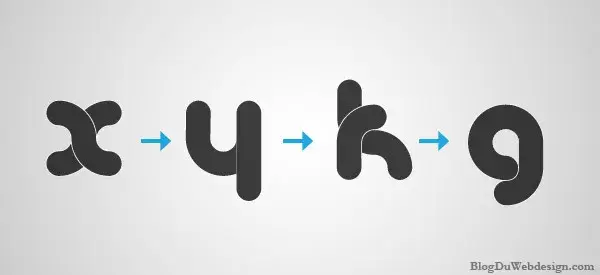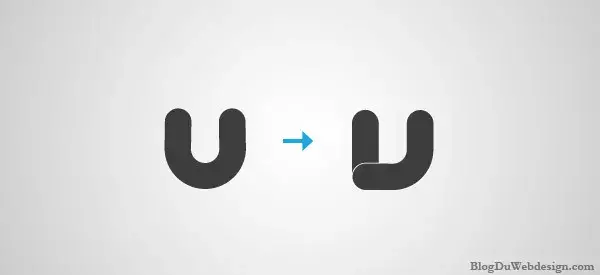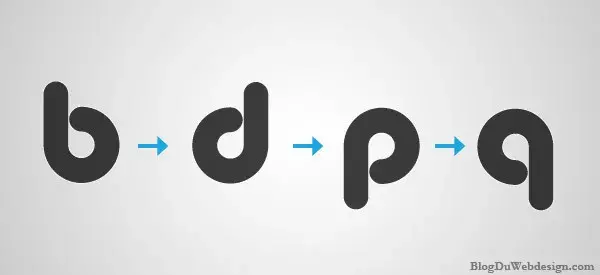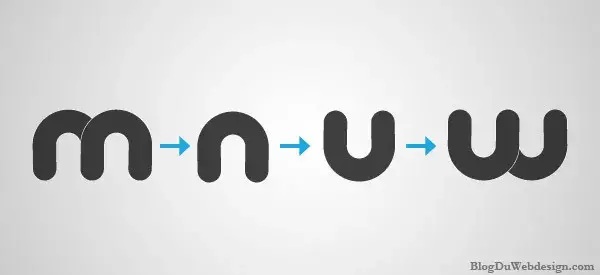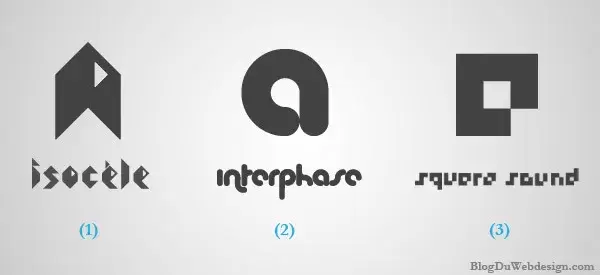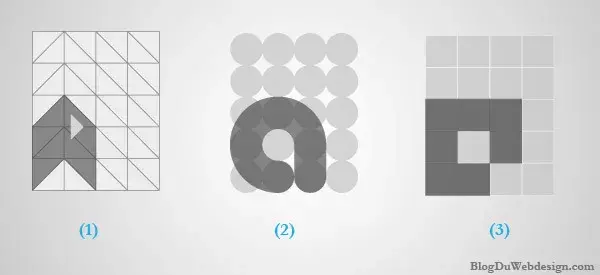
Comment créer et trouver sa typographie ?
Nous arrivons désormais à la moitié de notre dossier sur la typographie ! Cette semaine découvrez comment créer sa propre police à l'aide de nos conseils et également où trouver des fonts libres et contemporaines sur le web, avec une s&eacu
Comment créer sa typographie
Je vais vous montrer la méthode que j’utilise pour créer des typographies, bien entendu je ne suis pas typographe loin de là, c’est seulement en tant que conseiller que je vais expliquer mon travail. Pour créer une police complète et fonctionnelle cela demande beaucoup de techniques et de savoir faire dans ce domaine. Pour commencer, j’utilise le logiciel d’Illustrator qui me permet de créer des formes vectorielles et ainsi jouer avec les lettres et les tracés autant que je le désir. La création d’une typographie vient pour répondre à un besoin, créer une identité pour une marque, personnaliser un visuel graphique, exprimer des valeurs, etc.
Dans les 3 exemples ci dessus, j’ai voulu donner à chaque fois un caractère à la lettre: (1) jouer sur la construction en triangle pour connoter le pliage et l’origami. (2) Une lettre arrondie créée par le déplacement de 2 cercles. (3) Contraindre une police en pixel à tenir par du 3×3. Pour chaque création je me base sur une grille de construction que j’établis dès le début et qui va me permettre de construire et dessiner chaque lettre par la suite selon le principe que j’ai décidé.
Ensuite arrive les recherches, lettre par lettre, c’est à ce moment là que votre fichier AI commence à se remplir un peu partout entre les caractères faciles à réaliser et les autres comme le x, y, z … Car il faut toujours garder un équilibre entre Lisibilité, Cohérence et Originalité pour créer une typographie fonctionnelle, tout est question de composition et de déclinaison d’un même principe de construction.
Les lettres de bases
Il existe des caractères semblables qui permettent de réaliser facilement une grande partie de l’alphabet, par simple rotation ou effet miroir, on obtient d’autres lettres. Voici une liste de ces caractères:
Après nous avons les caractères qui posent généralement le plus de problèmes, par la cohérence (selon le système de construction choisi) et par la lisibilité. (u et v)
Autre Solution pour créer sa typo
Pour compléter !
Voici un visuel créé par Julien Hansen, qui permet de trouver sa typographie par un schéma simple, selon la réalisation que l’on doit réaliser (Logotype, affiche, ect) nous sommes guidé sur une typographie qui peut convenir. Cliquez sur l’image pour voir en grand.